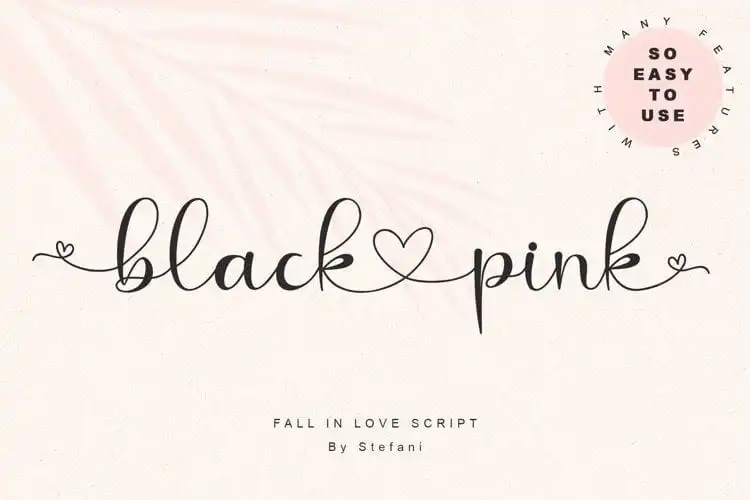
Black Love Pink Calligraphy Font – Download Grátis
A Black Love Pink Calligraphy Font é uma elegante fonte em letra cursiva que cativará os amantes do estilo elegante e moderno. Desenvolvida pela designer Stefani Letter, ela mantém sua influência clássica da escrita de arte ao mesmo tempo que se destaca como algo fresco e atual. Seus caracteres delicados e sofisticados são perfeitos para qualquer projeto gráfico que busque um toque romântico. Esta fonte é fácil de usar, bastando apenas adicionar sinais (–,++,–) em frente, no meio ou atrás dos caracteres revelando suas características únicas. O fato de ser PUA codificado significa que você pode acessar todos os gráficos e alternativas com facilidade! Além disso, oferece uma variedade de linhas básicas, belos gráficos e alternativas estilizadas para proporcionar um toque único aos seus projetos. Perfecta para criar designs românticos ou delicados sem esforço, a Black Love Pink Calligraphy Font é o seu parceiro perfeito na arte do design.